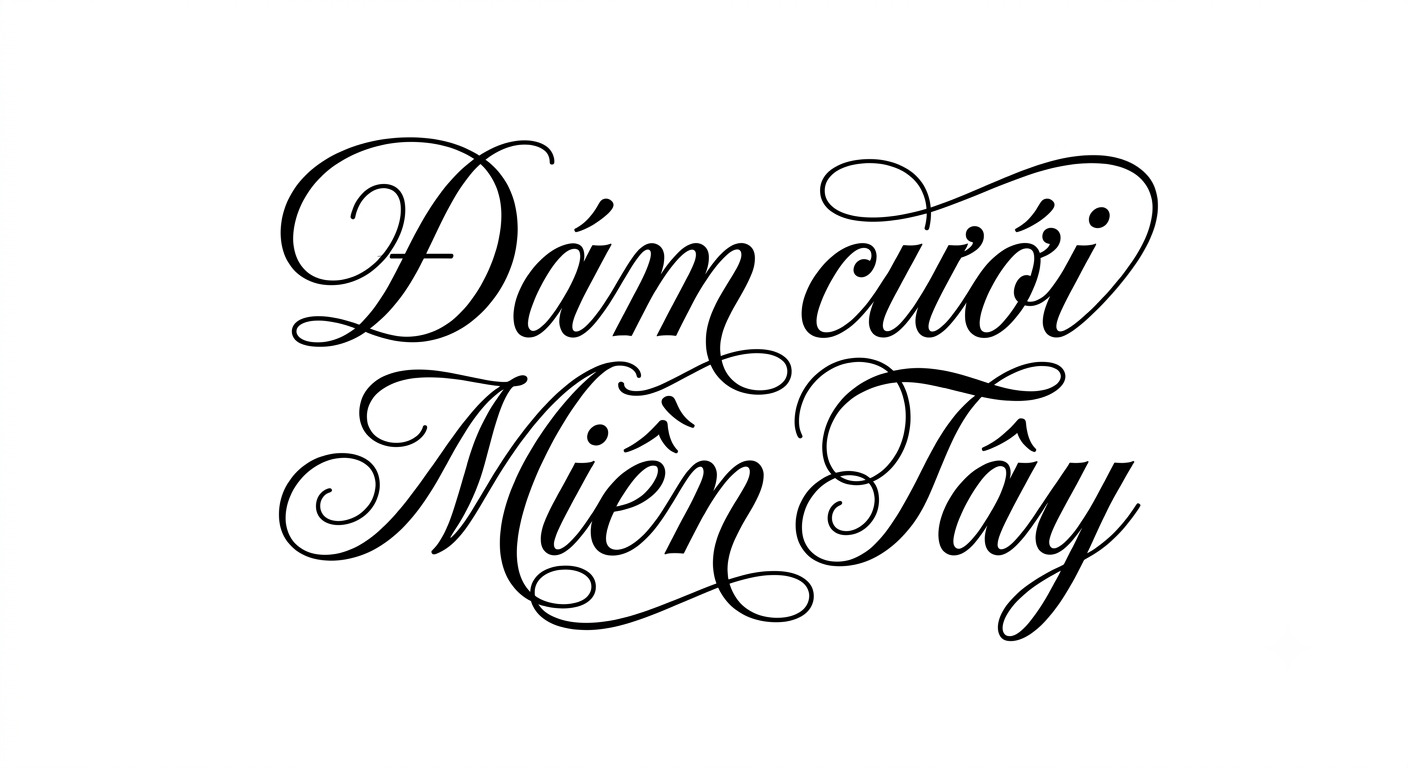
Tải 10+ bộ Font Wedding Việt hóa sắc nét chuyên cho thiết kế thiệp cưới và bao bì quà tặng
Nhiều designer tìm Font Wedding Việt hóa thường gặp lỗi thiếu dấu tiếng Việt ở tên cô dâu chú rể hoặc các nét chữ bay bổng bị vỡ khi phóng lớn để in thiệp cưới cao cấp. Những lỗi kỹ thuật này khiến thiết kế mất đi vẻ lãng mạn, làm giảm sự tinh tế và trang trọng của ấn phẩm trong ngày trọng đại.
Xưởng In Viva chia sẻ bộ Font Wedding Việt hóa sắc nét, hỗ trợ hiệu quả cho quá trình thiết kế thiệp cưới, bao bì quà tặng và các sản phẩm in ấn cao cấp theo phong cách sang trọng, tinh tế.
Font Wedding là gì?
Font Wedding là nhóm các phông chữ mang phong cách lãng mạn, thanh lịch và trang trọng, được thiết kế chuyên biệt cho các ấn phẩm ngày cưới, lễ kỷ niệm và quà tặng đính ước. Phông chữ cưới thường thuộc dòng Calligraphy Script (thư pháp hiện đại) với các nét nối mềm mại hoặc dòng Serif cổ điển quý phái. Đường nét chữ uyển chuyển như dải lụa, thể hiện sự gắn kết bền chặt, mang lại không khí ấm áp và thiêng liêng cho không gian ngày vui.
Điểm quan trọng trong các bản thiết kế cưới tại Việt Nam là việc thể hiện tên riêng của hai bên gia đình và cô dâu chú rể. Các bộ phông chữ quốc tế khi chưa được tinh chỉnh thường làm dấu hỏi, ngã, nặng bị lệch hoặc va chạm vào các đường tà uốn lượn (swashes). Bộ Font chữ Wedding đẹp do In Viva chọn lọc đã được xử lý dấu thanh tiếng Việt một cách chỉn chu theo chuẩn Unicode. Các dấu thanh được bố trí khoảng cách hợp lý, giúp giữ trọn vẹn nét duyên dáng của bộ chữ mà không gây cảm giác rối mắt khi dàn trang.
Font Wedding đẹp 01
Font Wedding đep 01
Lưu ý: Phông chữ cưới thường có nhiều nét thanh mảnh bay bổng. Khi in ấn trên giấy mỹ thuật sẫm màu, bạn nên ưu tiên kết hợp kỹ thuật ép kim nhũ vàng hoặc nhũ bạc mờ để tôn vinh sự lộng lẫy và trang nhã của chữ viết.
5 ứng dụng Font Wedding Việt hóa trong thiết kế và in ấn
Với phong cách mềm mại, lãng mạn cùng các đường nét chữ viết tay uyển chuyển, Font Wedding Việt hóa được ứng dụng linh hoạt trên nhiều sản phẩm cưới, bao bì và quà tặng cao cấp:
• Thiết kế thiệp cưới và thiệp mời sự kiện: Font Wedding phù hợp để thể hiện tên cô dâu chú rể, tiêu đề lễ cưới hoặc lời chúc trên thiệp giấy mỹ thuật. Các nét chữ bay bổng giúp thiết kế tạo cảm giác sang trọng, lãng mạn và mang dấu ấn cá nhân.
• In ấn hộp quà cưới và bao bì quà tặng: Font Wedding có thể sử dụng trên hộp đựng quà cưới, hộp bánh, hộp rượu hoặc hộp quà tri ân khách mời. Khi kết hợp cùng ép kim, dập nổi hoặc phủ UV, kiểu chữ giúp sản phẩm trở nên tinh tế hơn.
• Trang trí sổ ký tên và phụ kiện lễ cưới: Các dòng chữ sử dụng Font Wedding trên sổ ký tên, bảng welcome, bảng hướng dẫn bàn tiệc giúp không gian tiệc cưới đồng bộ và thể hiện phong cách riêng của cặp đôi.
• Thiết kế nhãn chai rượu vang và quà tặng kỷ niệm: Font Wedding phù hợp để in tên, ngày cưới hoặc thông điệp lên nhãn chai rượu, ly sứ, nến thơm và các món quà nhỏ dành tặng khách mời.
• Gia công túi giấy và bộ nhận diện sự kiện cưới: Logo hoặc tên sự kiện sử dụng Font Wedding trên túi giấy Ivory, giấy mỹ thuật giúp các thương hiệu dịch vụ cưới, studio hoặc nhà hàng tiệc cưới tạo hình ảnh chuyên nghiệp hơn.
Font Wedding đep 02
5 lưu ý khi sử dụng Font Wedding Việt hóa trong sản xuất
Để Font Wedding Việt hóa giữ được vẻ đẹp mềm mại và độ sắc nét khi đưa vào in ấn thực tế, designer cần chú ý:
• Kiểm tra vị trí dấu tiếng Việt: Font Wedding thường có nhiều nét nối và ký tự cách điệu. Cần kiểm tra kỹ các dấu thanh trong tên riêng để tránh tình trạng dấu bị lệch hoặc chồng lên đường nét trang trí.
• Tối ưu đường Path khi gia công ép kim, dập nổi: Khi sử dụng Font Wedding làm logo hoặc tên cô dâu chú rể trên hộp quà, file thiết kế cần được xử lý vector để các nét cong, nét nối được thể hiện chính xác khi gia công.
• Điều chỉnh khoảng cách ký tự (Kerning): Các ký tự viết tay thường có độ nối cao. Designer nên cân chỉnh khoảng cách giữa từng chữ để tên riêng hoặc câu chúc trên thiệp có bố cục cân đối, dễ đọc.
Có, đội ngũ thiết kế của In Viva hỗ trợ tư vấn bố cục, lựa chọn Font Wedding và phương án gia công phù hợp khi khách hàng đặt sản xuất trực tiếp tại xưởng.